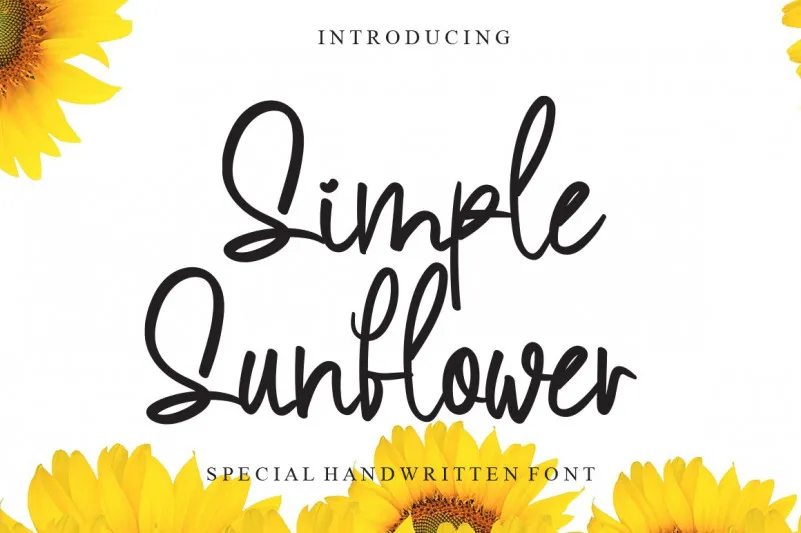
Esta é uma fonte escrita a mão, igualmente delicada e cursiva, perfeitamente adaptável para transmitir mensagens com confiança, autenticidade e encanto. Ela é ideal não apenas para cartões de aniversário, mas também para a criação de marcas, etiquetas e muito mais. Ideal para designers que desejam dar um toque personalizado em seus projetos de design gráfico, este estilo curioso de escrita naturalmente eleva os ideais criativos. Seja você uma designer gráfica ou simplesmente alguém com interesse na adicionar uma pitada única a suas criações, o ‘Simple Sunflower Font’ de LevinCreative é a fonte perfeita para seu portfólio. Se você gosta do estilo floral deste design artístico, pode querer explorar também outros recursos da mesma família, criando um visual único e personalizado. Essa fonte é uma ótima maneira de dar vida ao seu trabalho, garantindo que cada projeto seja memorável e inconfundível.